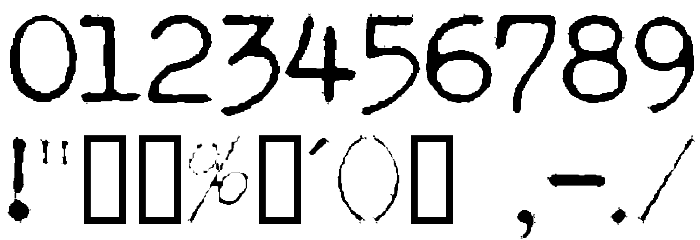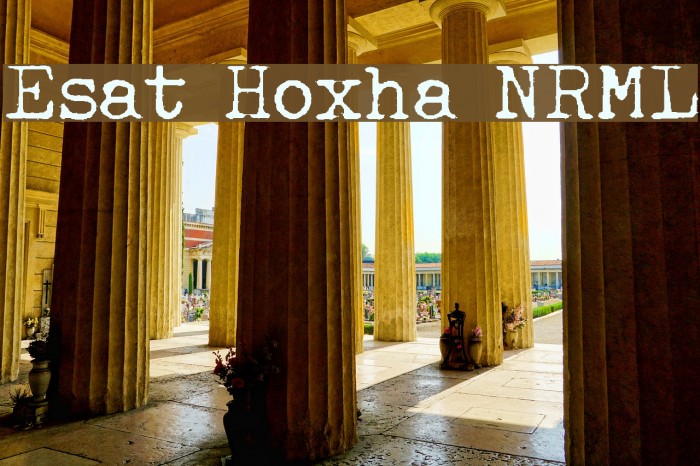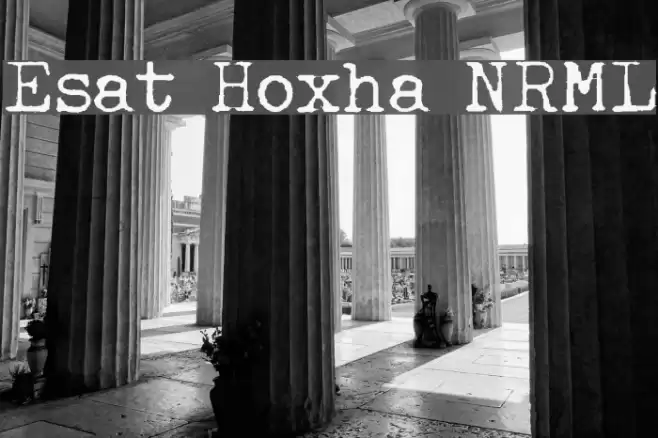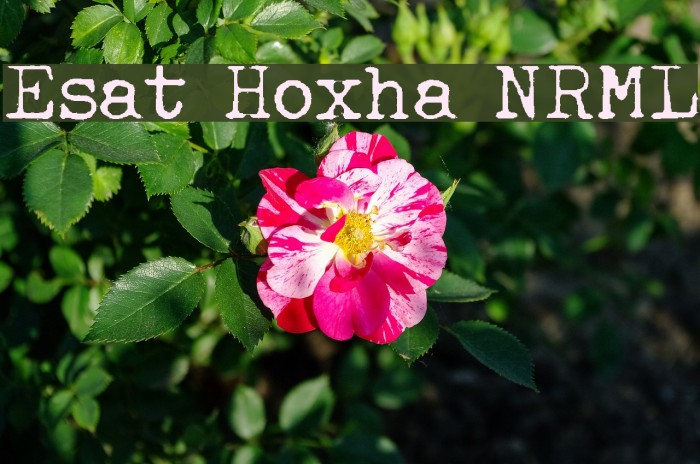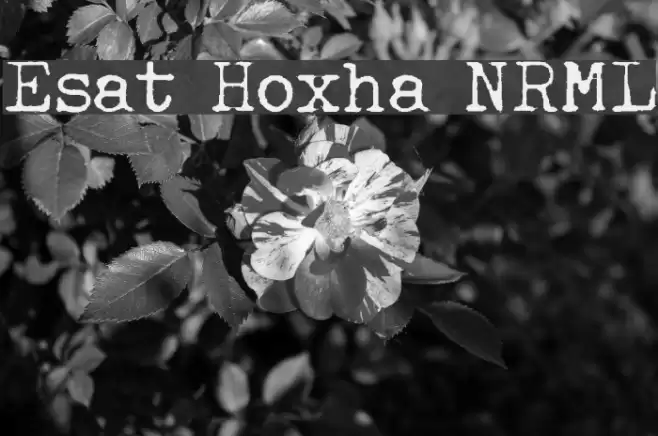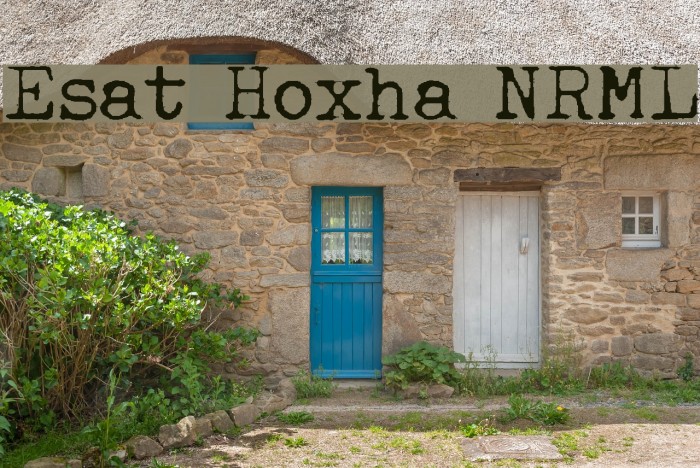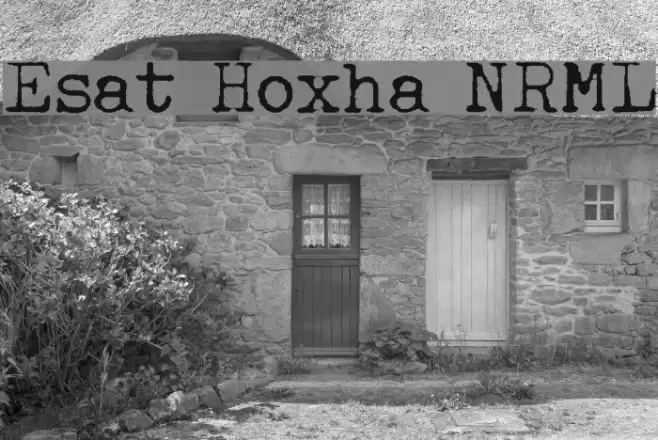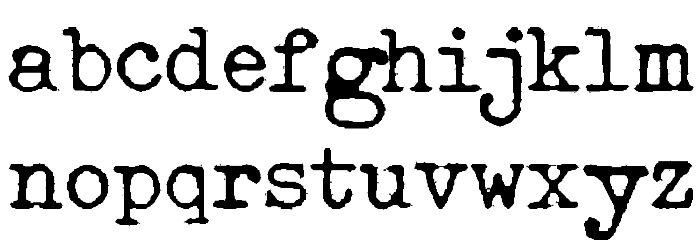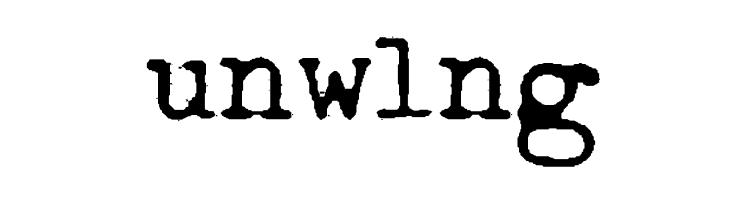
Esat Hoxha NRML Font
✎ Typewriter
| 分类 | Typewriter |
| 整体风格 | Vintage |
| 推荐项目 | Ideal for vintage-themed posters, retro branding, book covers, and creative projects that seek an authentic, nostalgic look. |